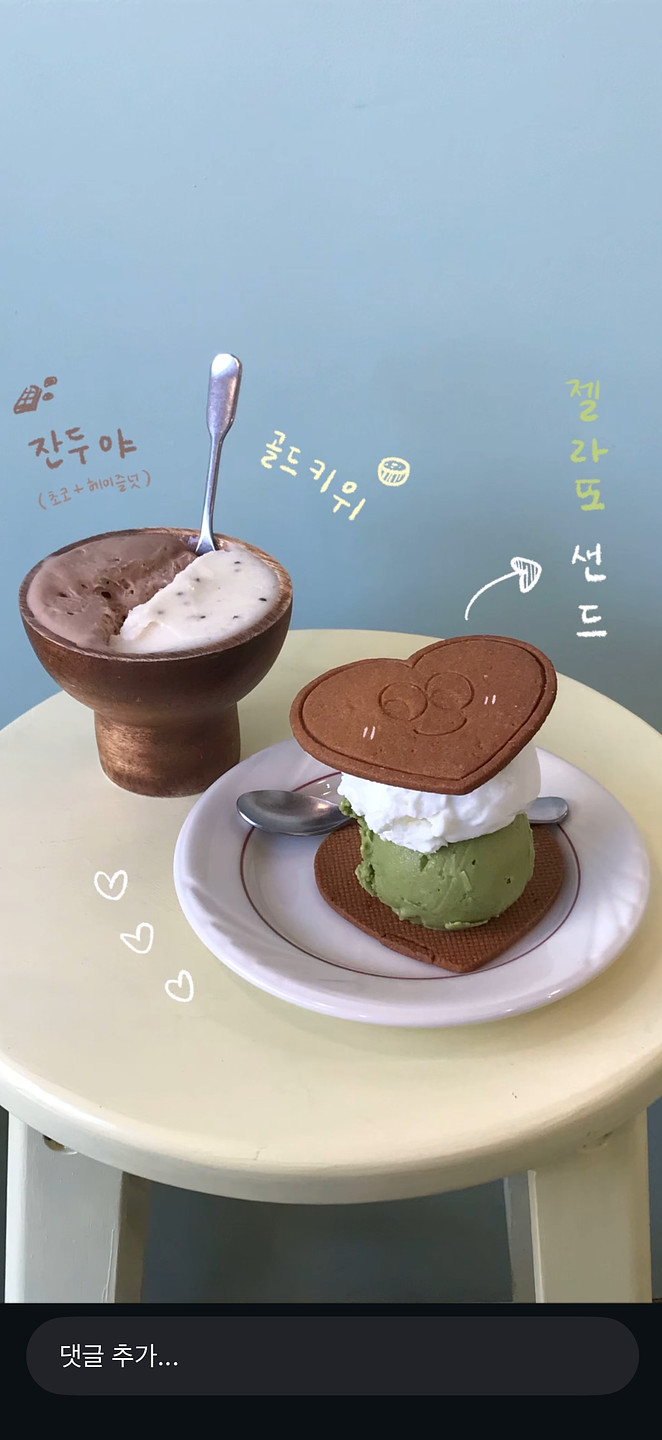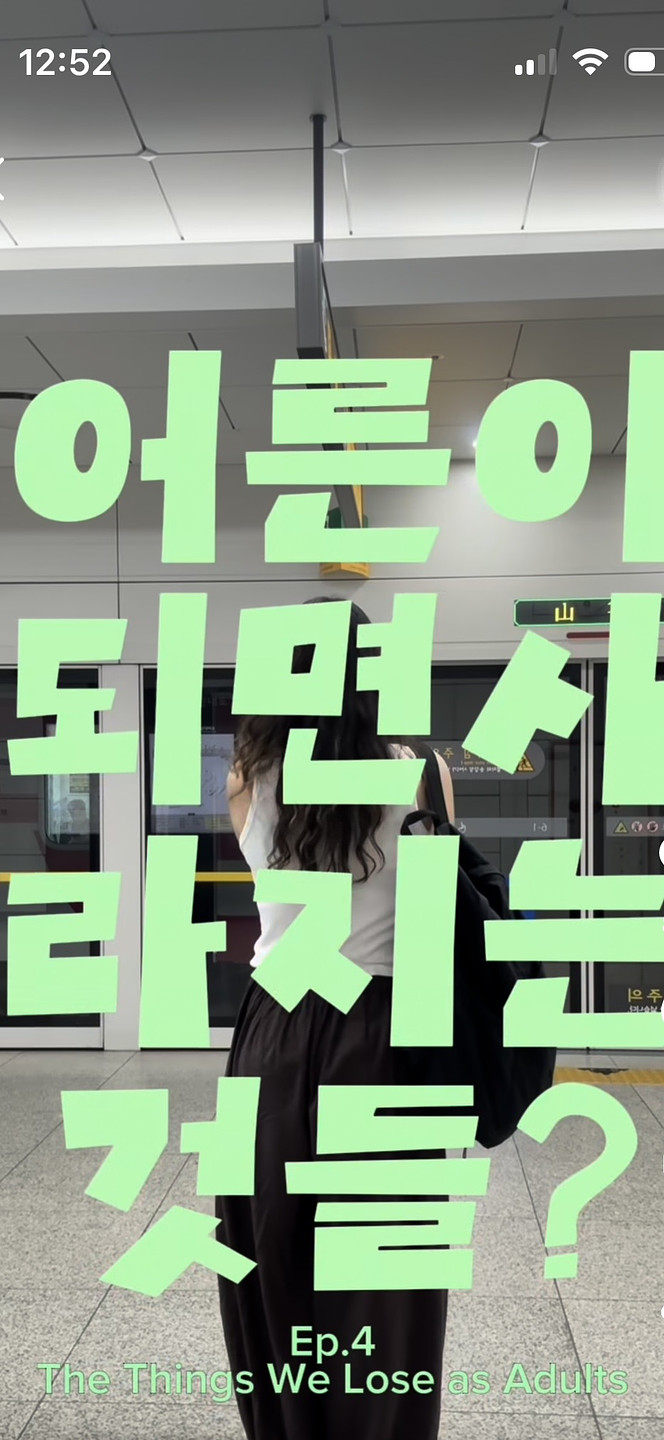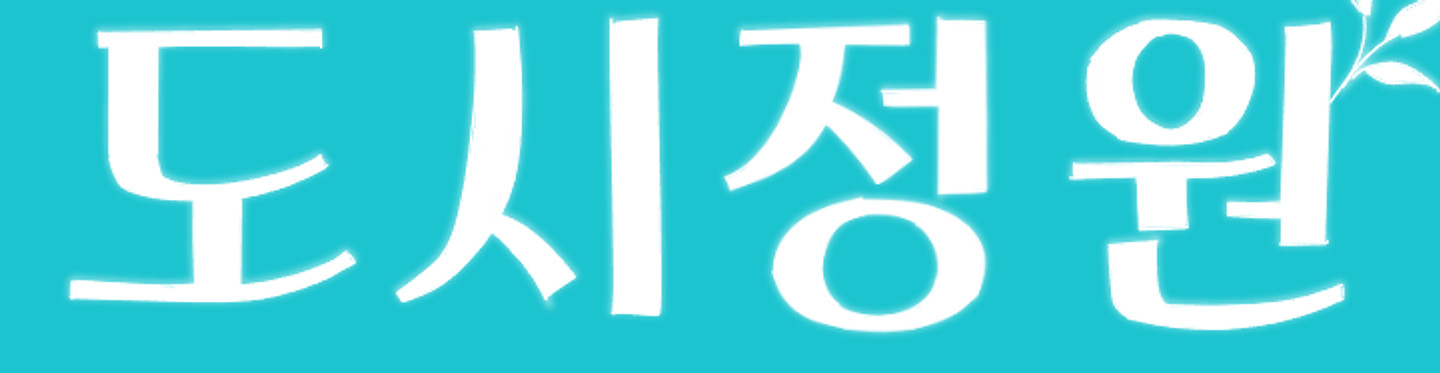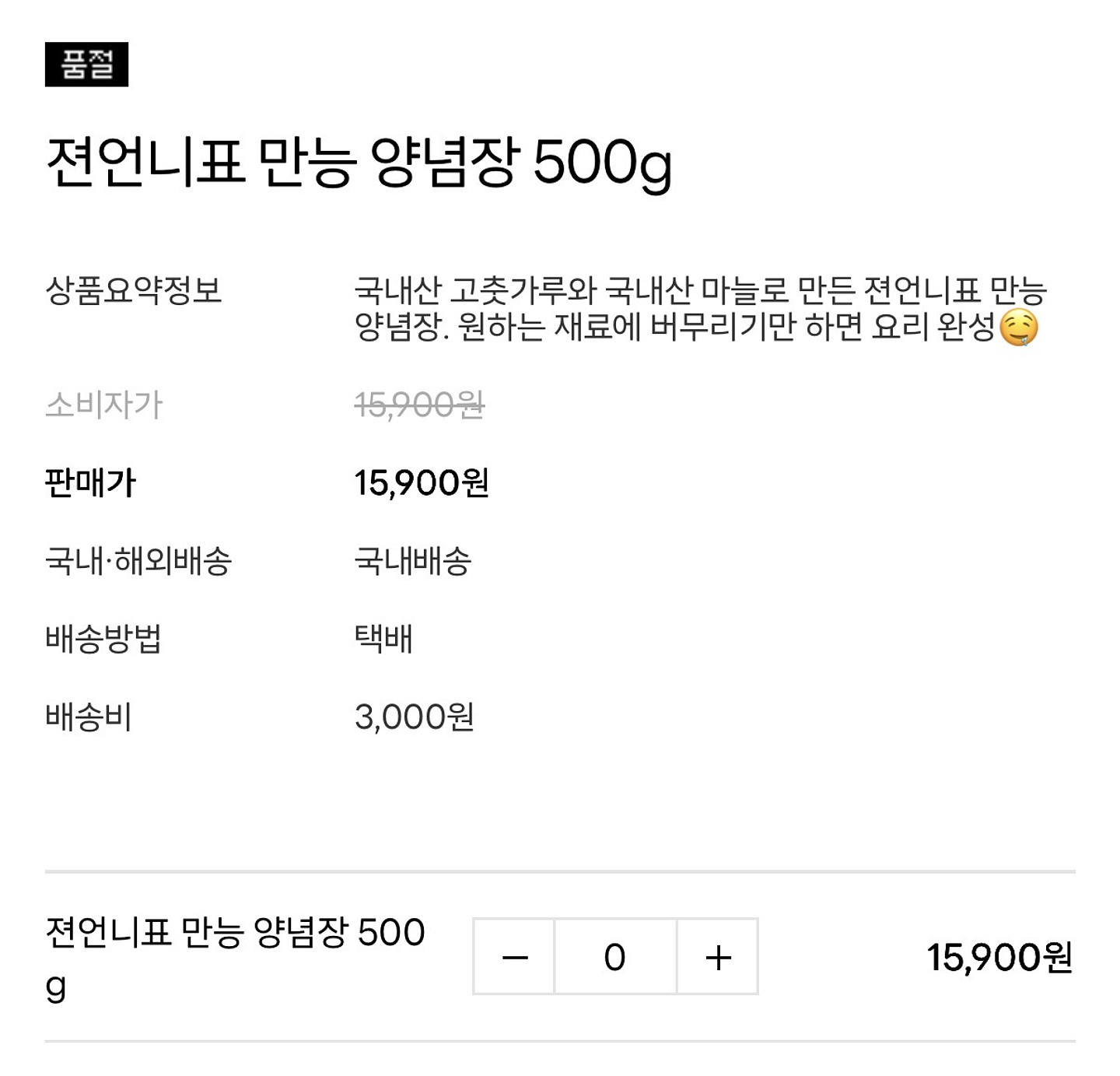
이거 무슨 폰트인가요???
혹시 무슨 폰투인지 알 수 있을까요?
이거 무슨 폰튼가용???
요거 무슨 폰트일까용??
요거 무슨 폰트 일까유???
ㅇ이랑 ㅎ이 살짝 틀어져있고 ㅅ의 뻗침이 없는게 너무 예뻐서 어떤 폰트인지 궁금하네요 ㅠㅠ
이 폰트 뭘까유ㅠ
이거 뭔가요?
폰트 이름 궁금해요!! 혹시 아시는 분 계실까요!!
HG꼬딕씨 << 아니에요ㅜ 꼬딕씨라고 답변 달지마세용 분홍색 박스에 들어가있는 폰트 뭔지 아시는 분 있나요? 처음에는 꼬딕씨인줄 알았는데 적어보니까 ㅍ,ㅋ,ㅅ 모양들도 다르고 영어 폰트도 다르네여 ㅠㅠ
SK나이츠 한글 마킹 폰트인데, 어떤 폰트인지 아시는 분 계신가요? 일단 산돌구름에 검색했을때는 똑같은 폰트는 안 나오는 것 같네요..
스캔한 폰트라 약간 깨져보이는데.. 어떤 폰트인지 정말 궁금합니다..!!
이거 무슨 폰트에요?ㅠㅠ